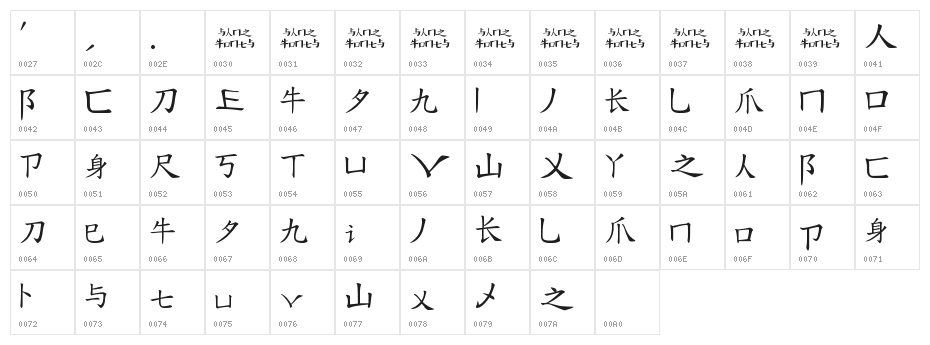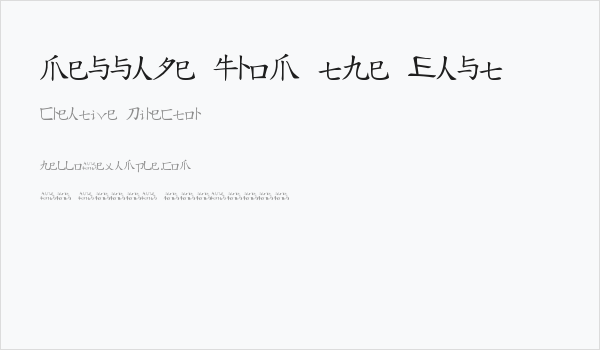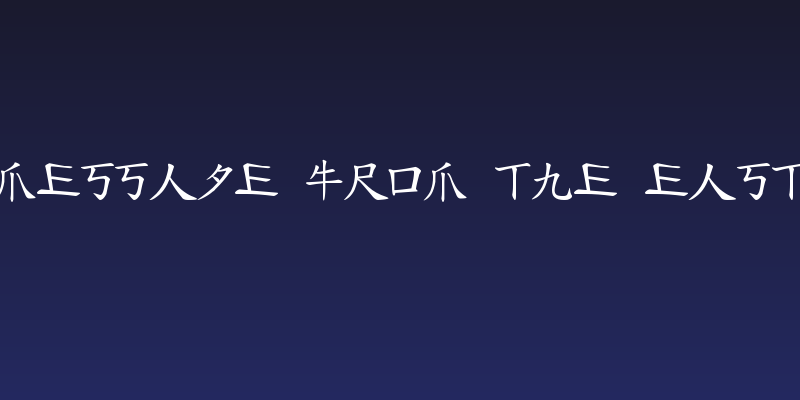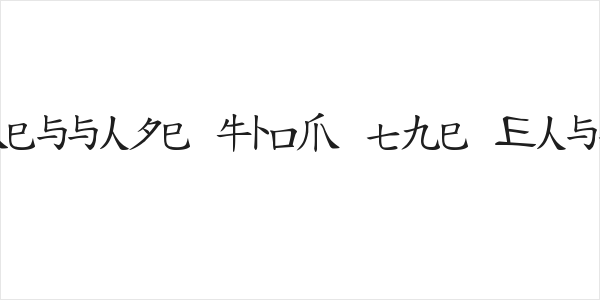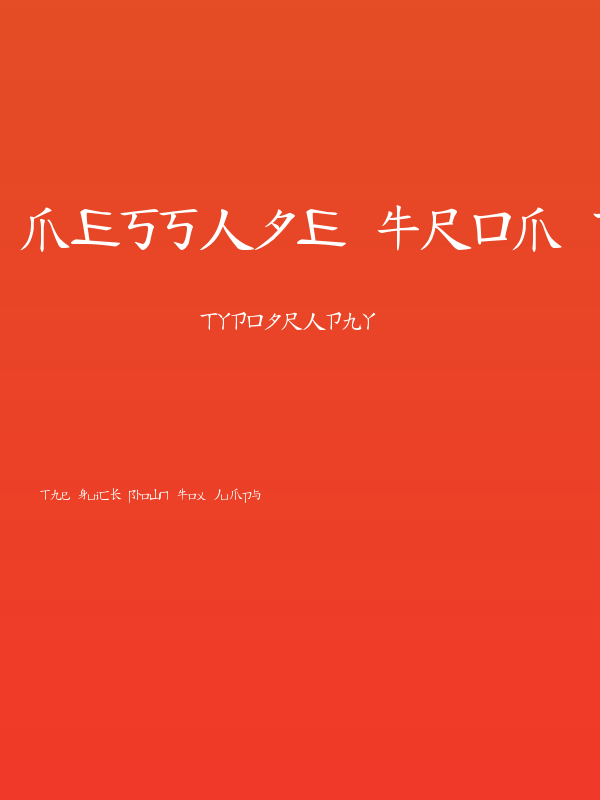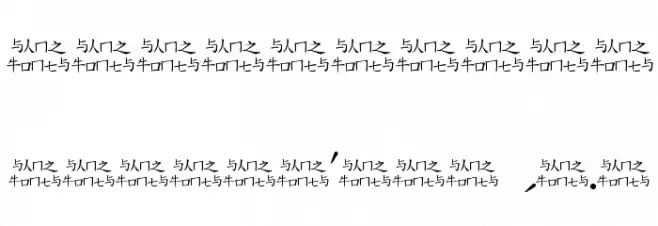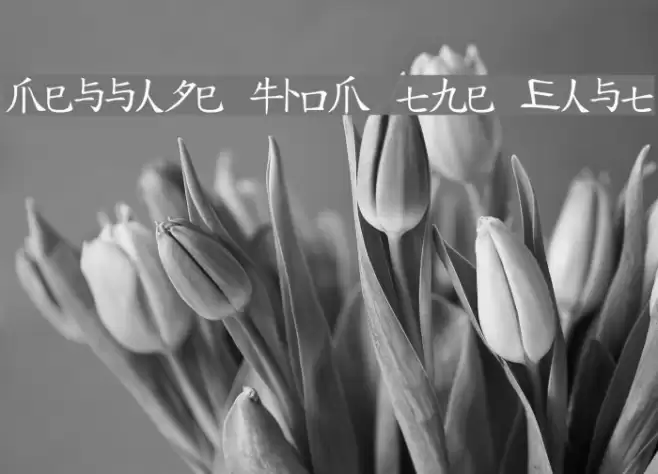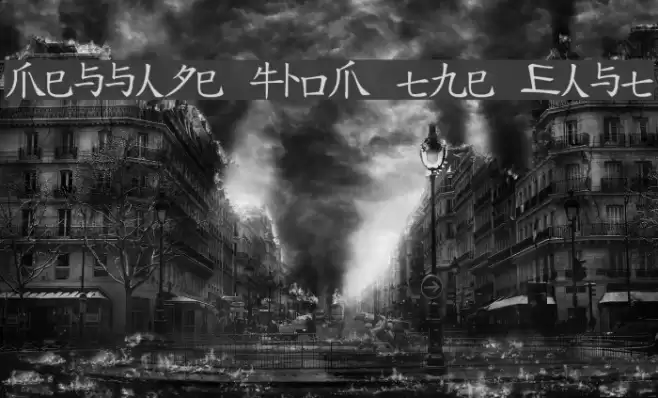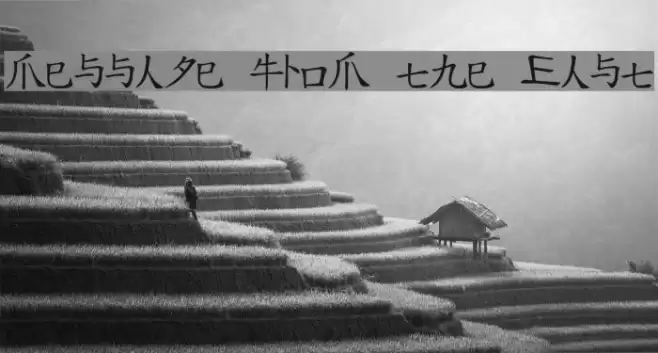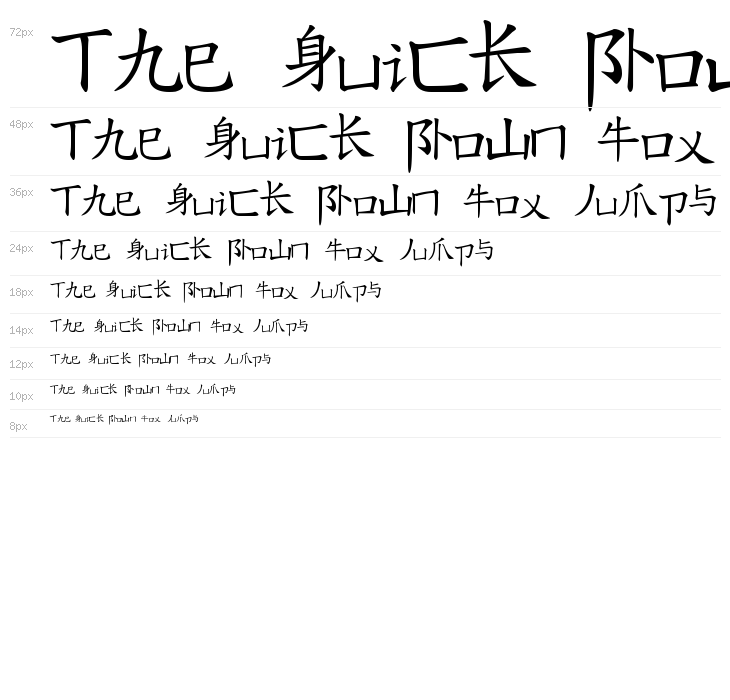
Message from the East Font
| Caso de uso | Logos, Headlines, Artistic projects |
| Proyectos propuestos | Ideal for cultural event posters, artistic invitations, or branding that seeks an exotic and sophisticated touch. |